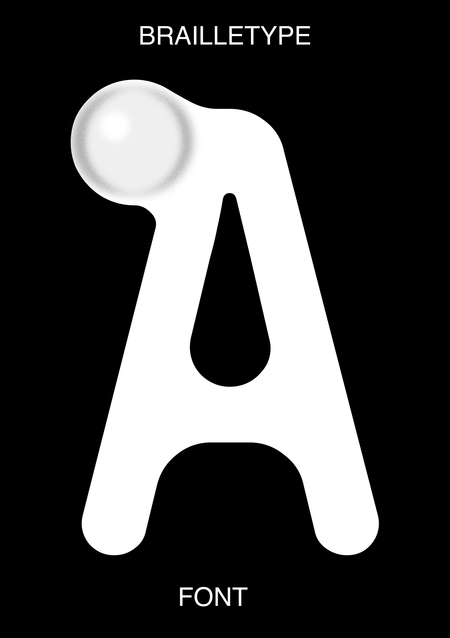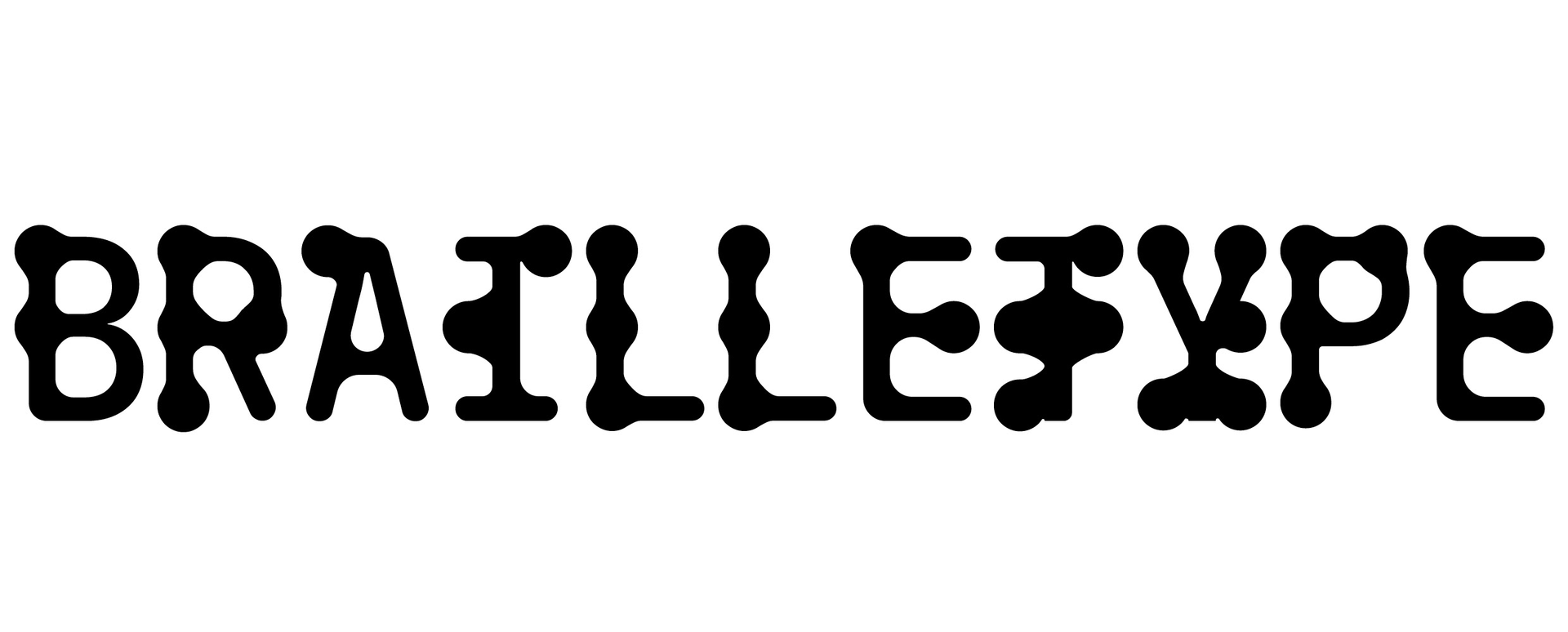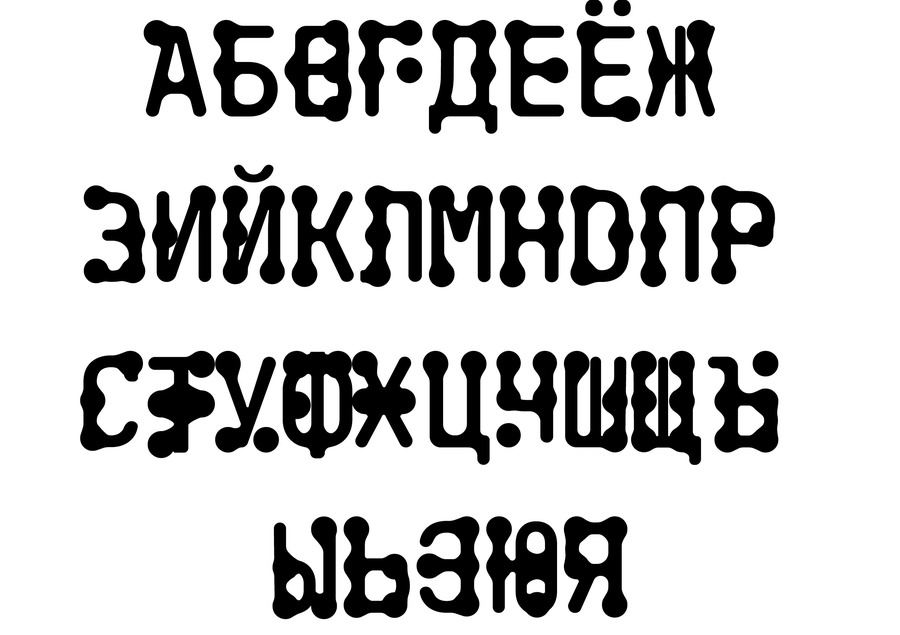
Brailletype — акцидентный шрифт, основанный на шрифте Брайля.
Шрифта Брайля — рельефно-точечный тактильный шрифт, предназначенный для письма и чтения незрячими и слабовидящими людьми.
«Шрифт для всех» — короткое описание данного шрифта. Предполагается, что таким шрифтом можно писать, как для зрячих, так и для слабовидящих и незрячих, достаточно лишь поверх печати выделить акцентные элементы на шрифте лаком или другим способом, сделав их объёмными.
За основу был взят моноширинный гротескный шрифт. Каждый акцентный элемент в символе соответствует верному расположению точки в шрифте Брайля для этого символа.
Шрифт Брайля иногда наносят с помощью квадратов, поэтому другая версия шрифта основана на интерпретации шрифта Брайля в таком виде.